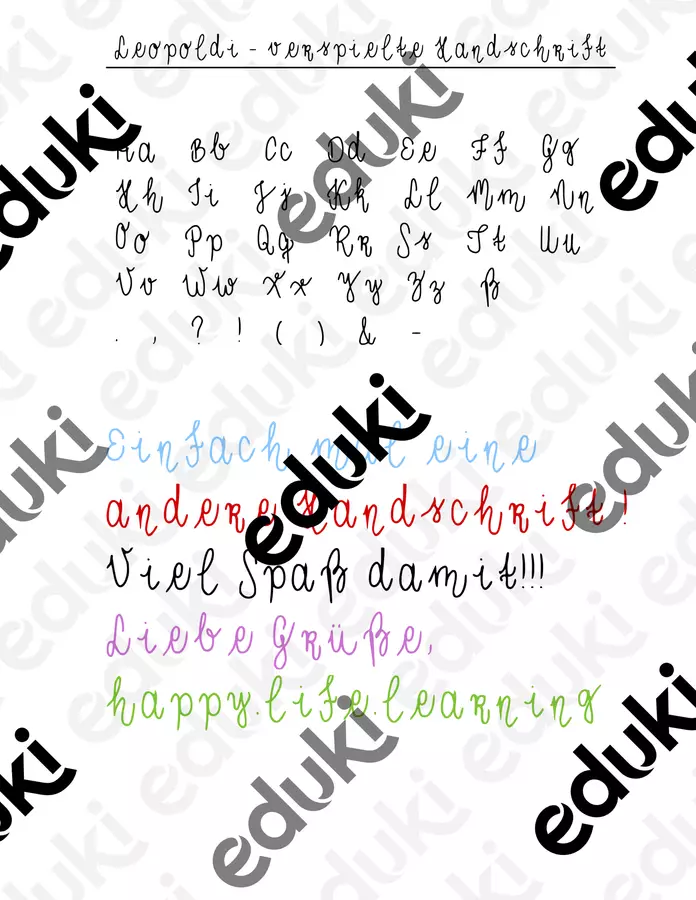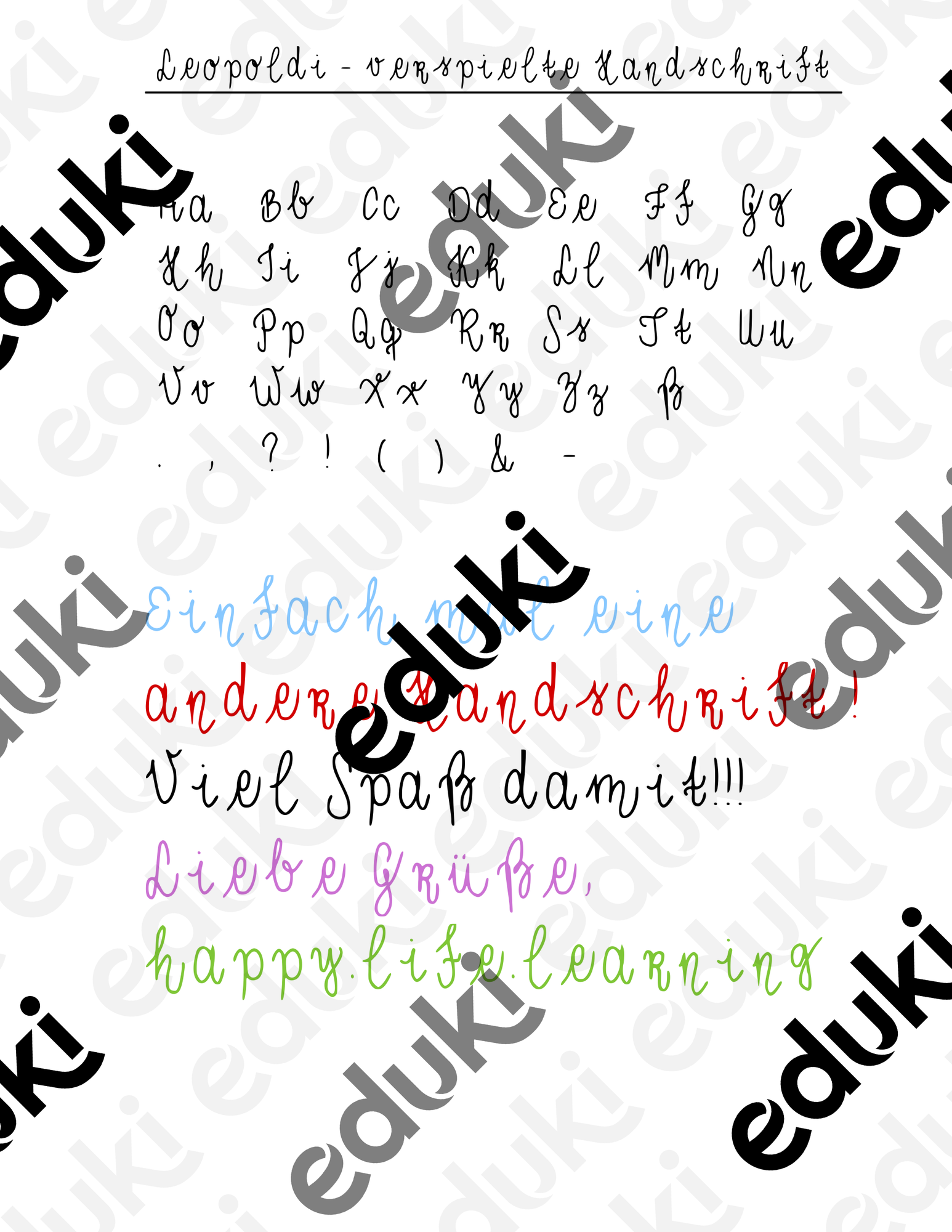
selbst erstellte Schriftarten - Leopoldi -  Schriftart zur kommerziellen Nutzung  - happy.life.learning - Deckblatt
Dieses Material bietet eine kreative Schriftart, die ideal für den Einsatz im Unterricht oder den privaten Gebrauch ist. Die Schrift „Leopoldi“ ist nicht nur ansprechend, sondern gestaltet selbst erstelltes Material individuell / peppt dieses auf verspielte Art und Weise auf.
Leopoldi -  Schriftart zur kommerziellen Nutzung